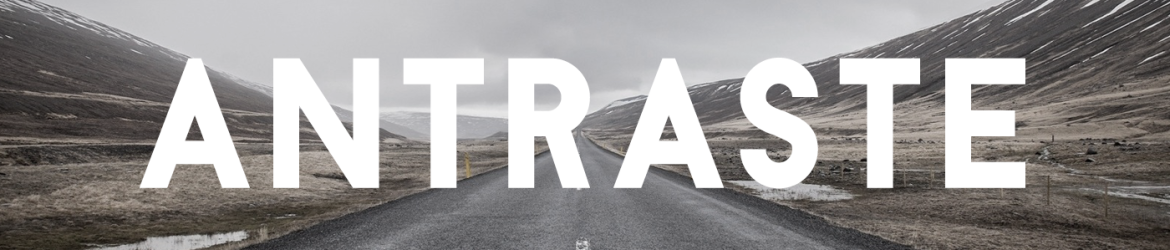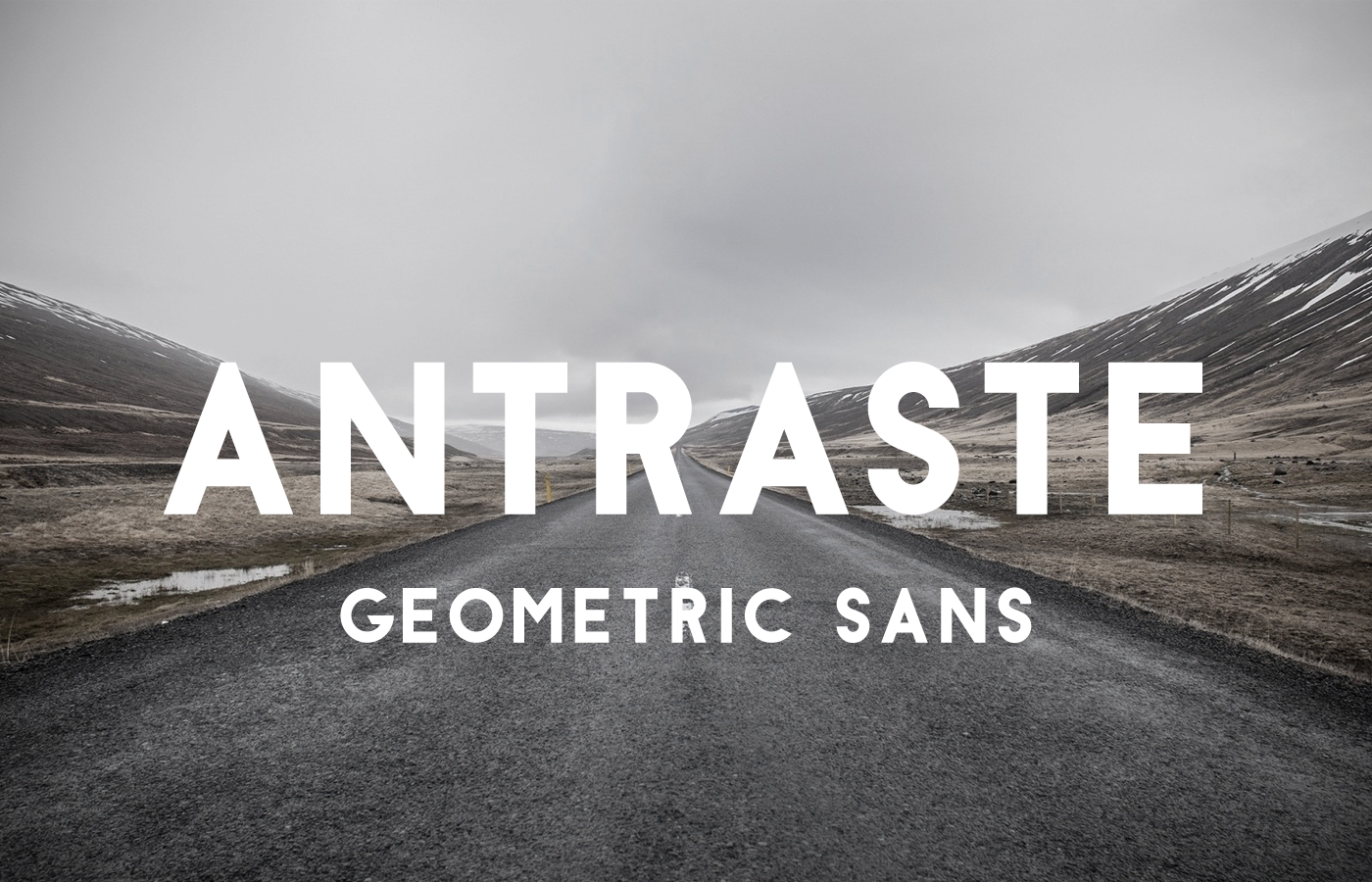
Antraste Font
Antraste é uma nova fonte sans serif que chega para dar o tom aos projetos digitais modernos. Lançada por Marco Ballarè, Antraste oferece um ar romântico e elegante com um forte apelo latineiro. A família de caracteres inclui Basic, Western, Central Euro e South Euro, fazendo-a uma escolha ideal para uma ampla gama de projetos visuais. Suave e sofisticada, Antraste foi projetada especialmente para aparições de destaque, ilustrações, posters, logotipos, camisetas com estampas ou até mesmo como cabeçalhos. Com seu ar elegante e criativo, é perfeita para qualquer projeto visual que deseja destacar-se. Estamos ansiosos para você explorar a Antraste Font, uma fonte sans serif do tipo moderno e versátil que será definitivamente uma opção favorita no seu armário de recursos gráficos.